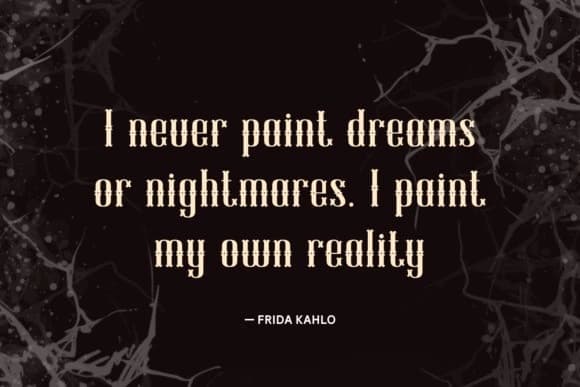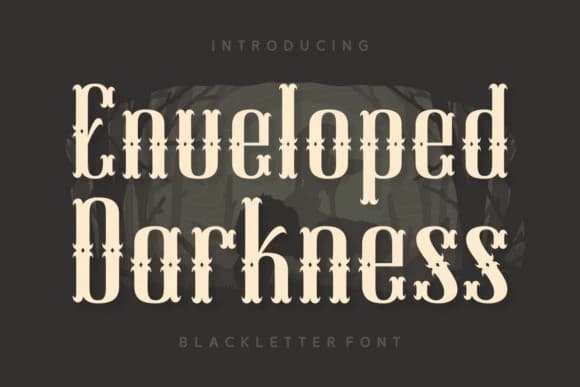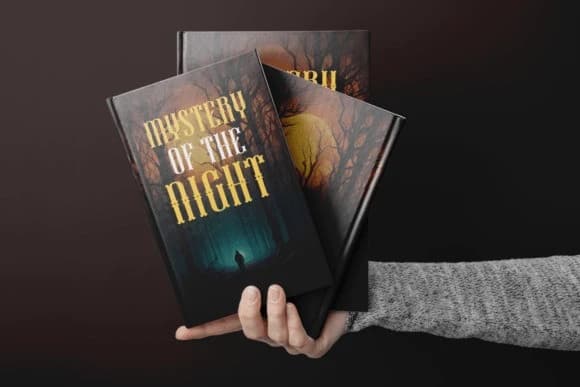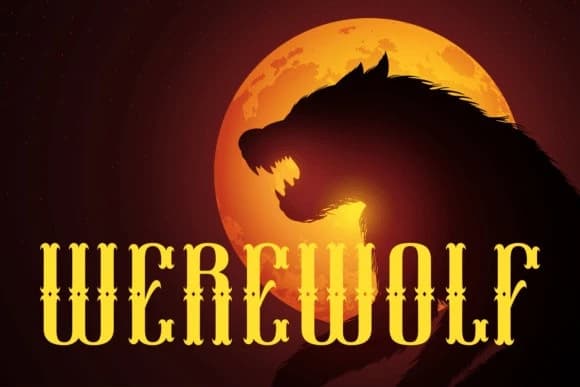
Enveloped Darkness Font, merak uyandıran bir gizemle dolu vintage bir blackletter yazı karakteri. İncelikli işçiliği klasik tipografiye saygı duruşunda bulunurken benzersiz bir dokunuş sunar. Bu çok yönlü font, web sitesi tasarımı için idealdir ve dergilerin sayfalarını canlandırır.
Enveloped Darkness Font, ilginç bir gizemle dolu antika bir gotik yazı tipi. İnce işçiliği klasik tipografiye saygı duruşunda bulunurken eşsiz bir dokunuş sunar. Bu çok yönlü yazı tipi, web sitesi tasarımı için idealdir ve dergilerin sayfalarını canlandırır